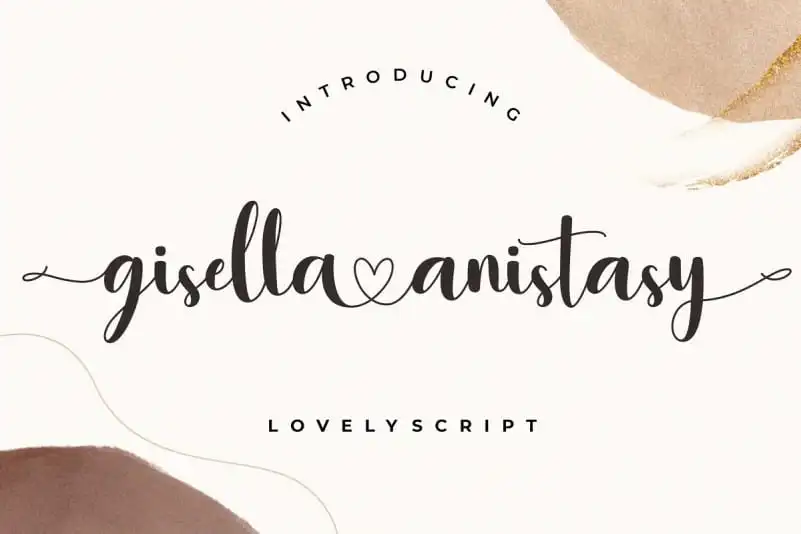
Gisella Anistasy Script Font – Fonte Grátis
Gisella Anistasy Script Font
A Gisella Anistasy Script Font é uma elegante tipografia script desenvolvida pela Creatype Studio. Com seu visual sofisticado, moderno e elegantemente contemporâneo, ela se destaca como a escolha perfeita para diversos tipos de projetos gráficos. Ideal tanto para o branding dos seus projetos quanto para trabalhos que exigem um toque autêntico da escrita à mão, a Gisella Anistasy Script Font é uma opção inigualável para criações variadas como logomarcas, design de casamentos, postagens nas redes sociais, anúncios e embalagens de produtos. Ela também brilha em designs de produto, etiquetas, fotografia, marca d’água, convites e materiais de estação, atendendo a uma ampla gama de necessidades gráficas onde um toque autêntico da escrita à mão é desejado. Este fonte oferece design para quem busca trazer um charme único aos seus projetos.